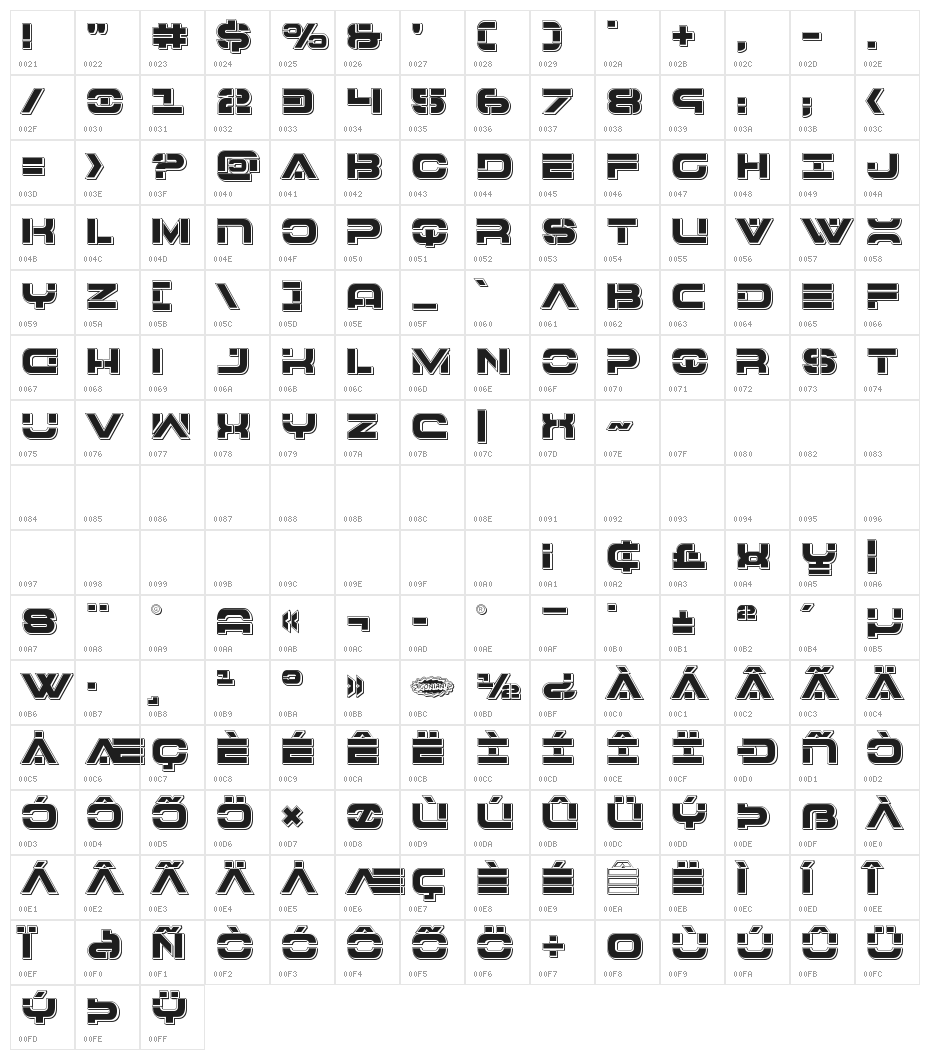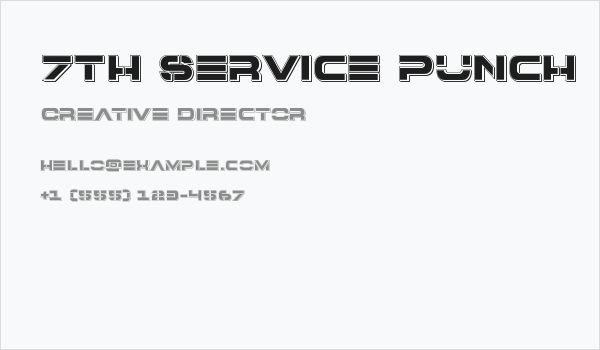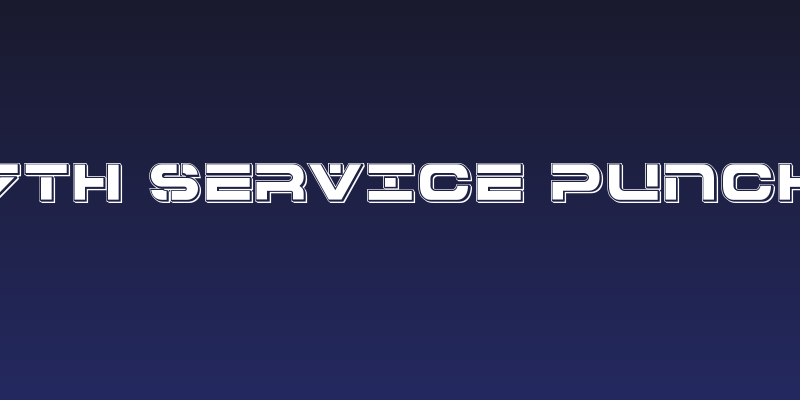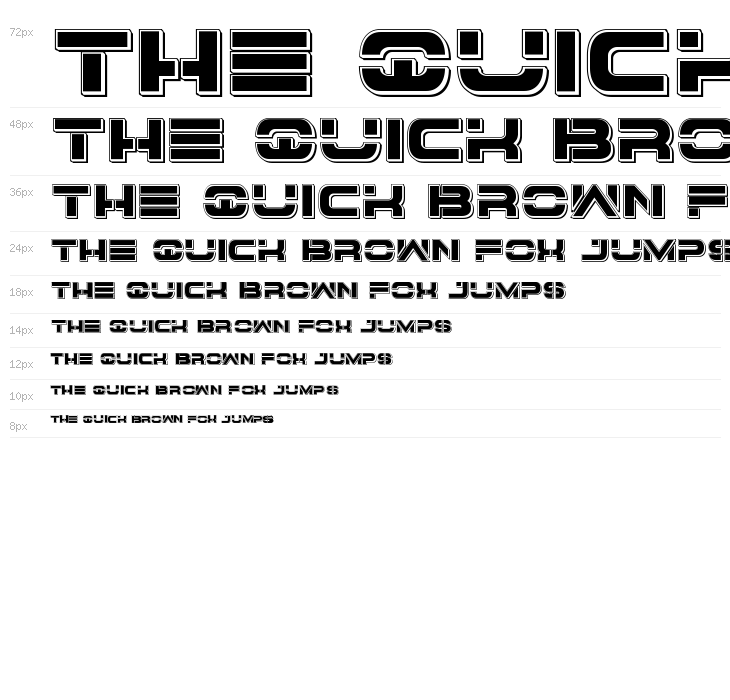
7th Service Punch Font
✎ Futuristic
| Vorgeschlagene Projekte | Ideal for sci-fi themed designs, tech branding, video game titles, and modern posters. |